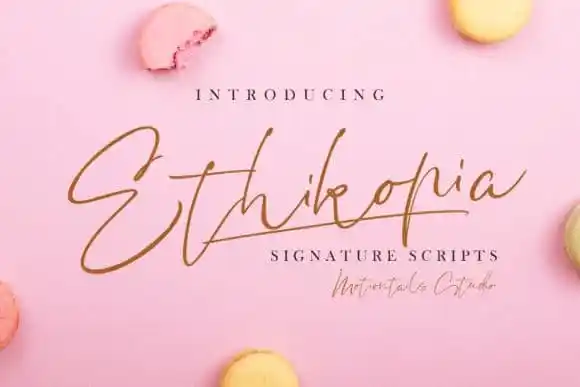
Ethikopia Handwritten Font – Download Grátis
A Ethikopia Handwritten Font é uma tipografia escrita a mão única e moderna criada pela Motiontailstudio. Este tipo de letra foi projetado para se tornar um verdadeiro preferido, potencialmente transformando cada ideia criativa de vocês em seu nível mais alto. Adaptada ao gosto contemporâneo dos designers de identidade visual, esta fonte escrita a mão transmite uma sensação descontraída e acolhedora que não é comum encontrar em outras tipografias. A elegância e o charme da Ethikopia são perfeitos para quem procura um elemento diferenciado nas criações gráficas. Seja para trabalhos de marca, design editorial ou até mesmo como adesivo de carro, esta fonte escrita a mão traz uma personalidade única que certamente será bem recebida. Como designer, você pode explorar novos caminhos criativos com Ethikopia Handwritten Font, tornando seus projetos ainda mais únicos e memoráveis.